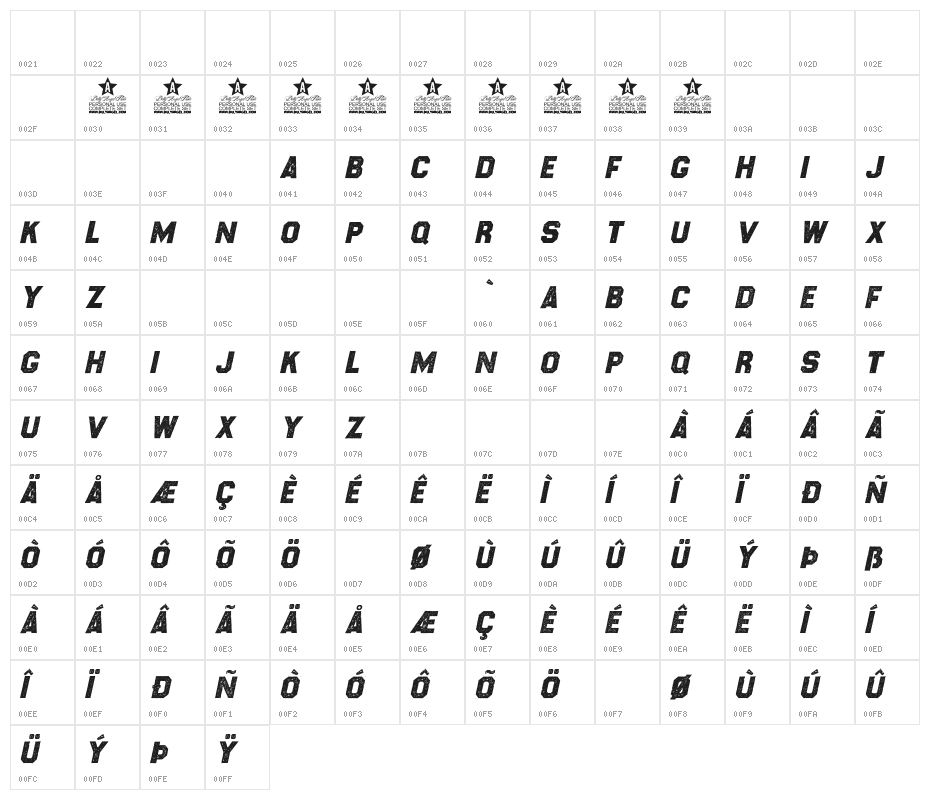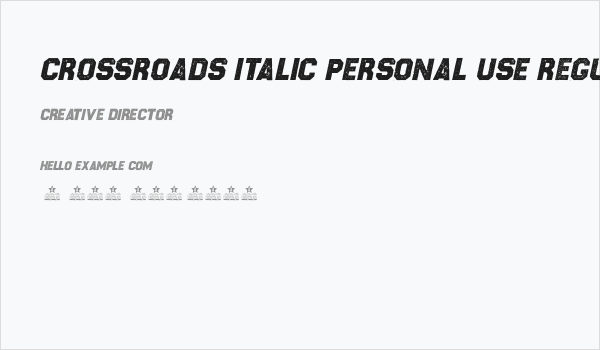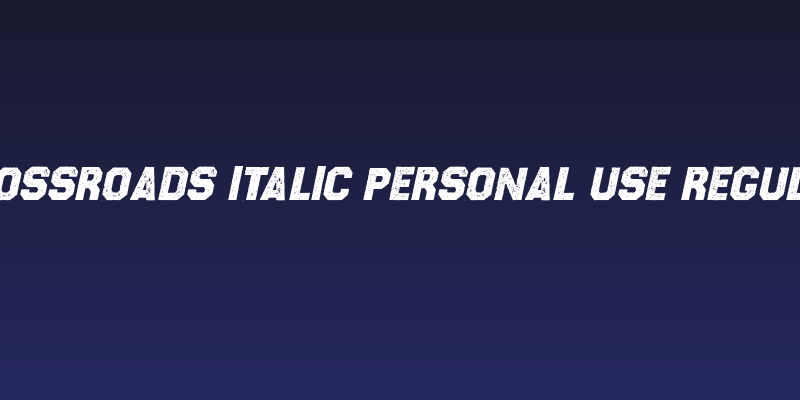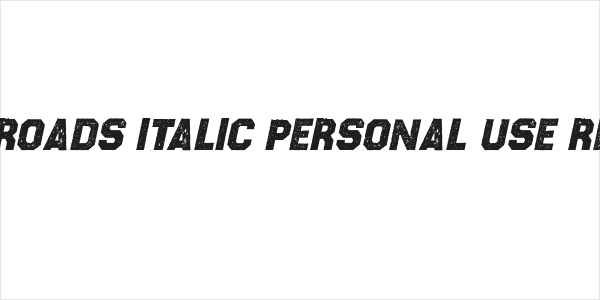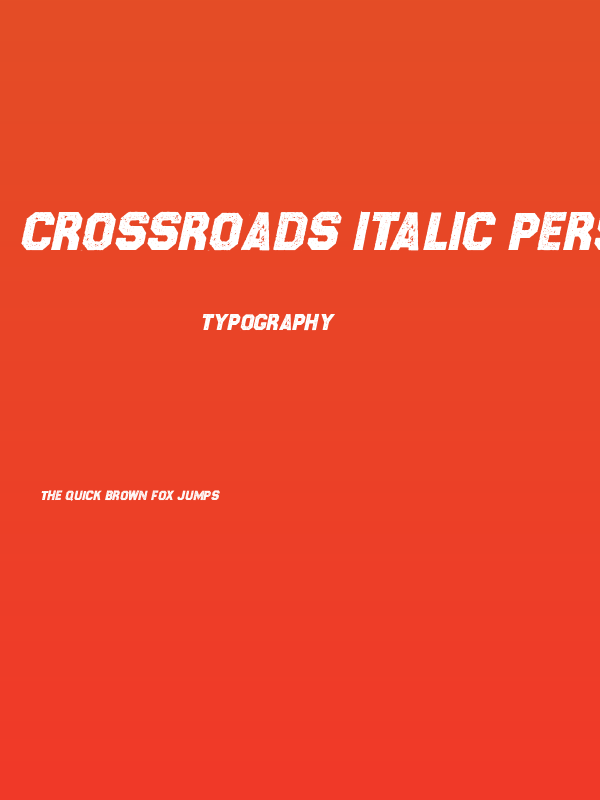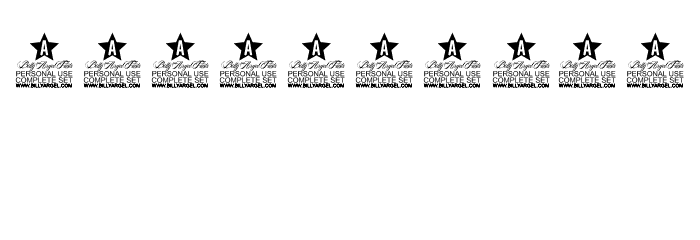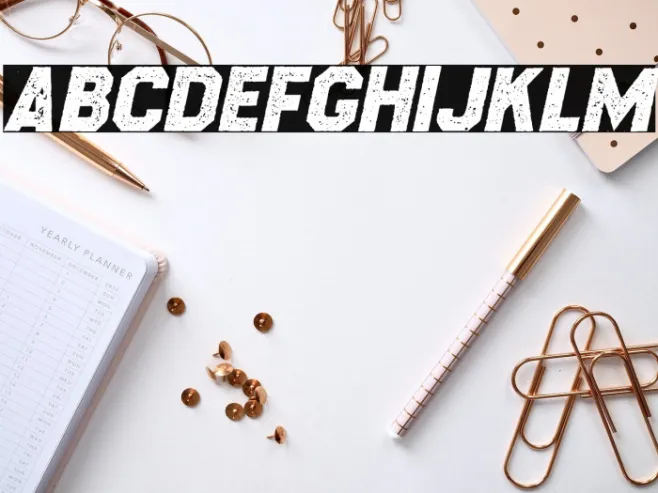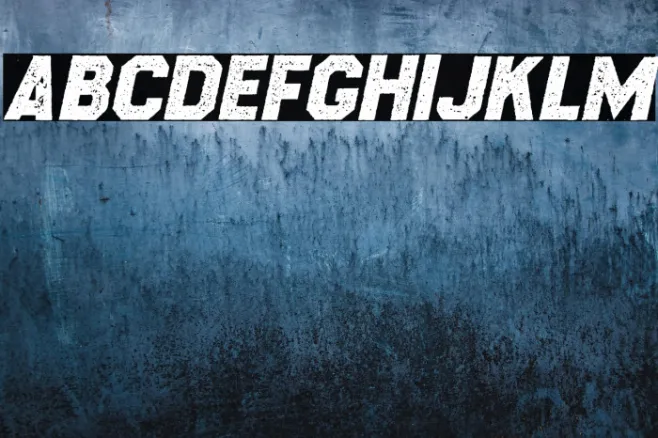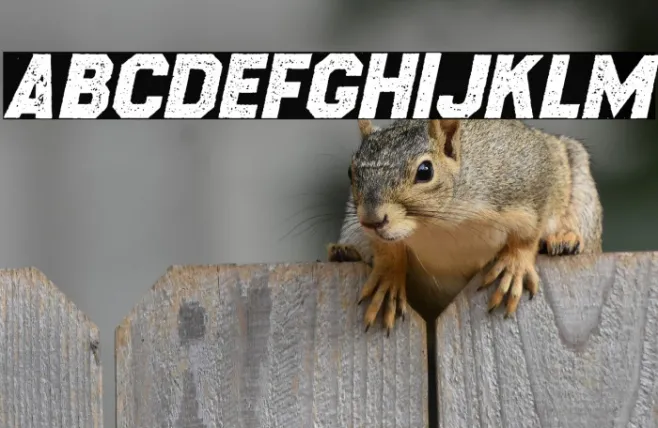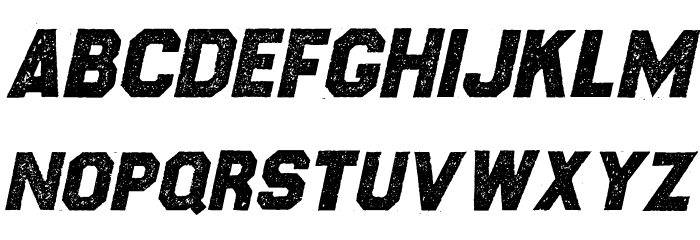
CROSSROADS ITALIC PERSONAL USE Regular Font
✎ Messy
| Kategorien | Messy |
| Gesamtstil | Vintage |
| Vorgeschlagene Projekte | Ideal for vintage-themed posters, retro branding, album covers, and signage that requires a bold statement. |